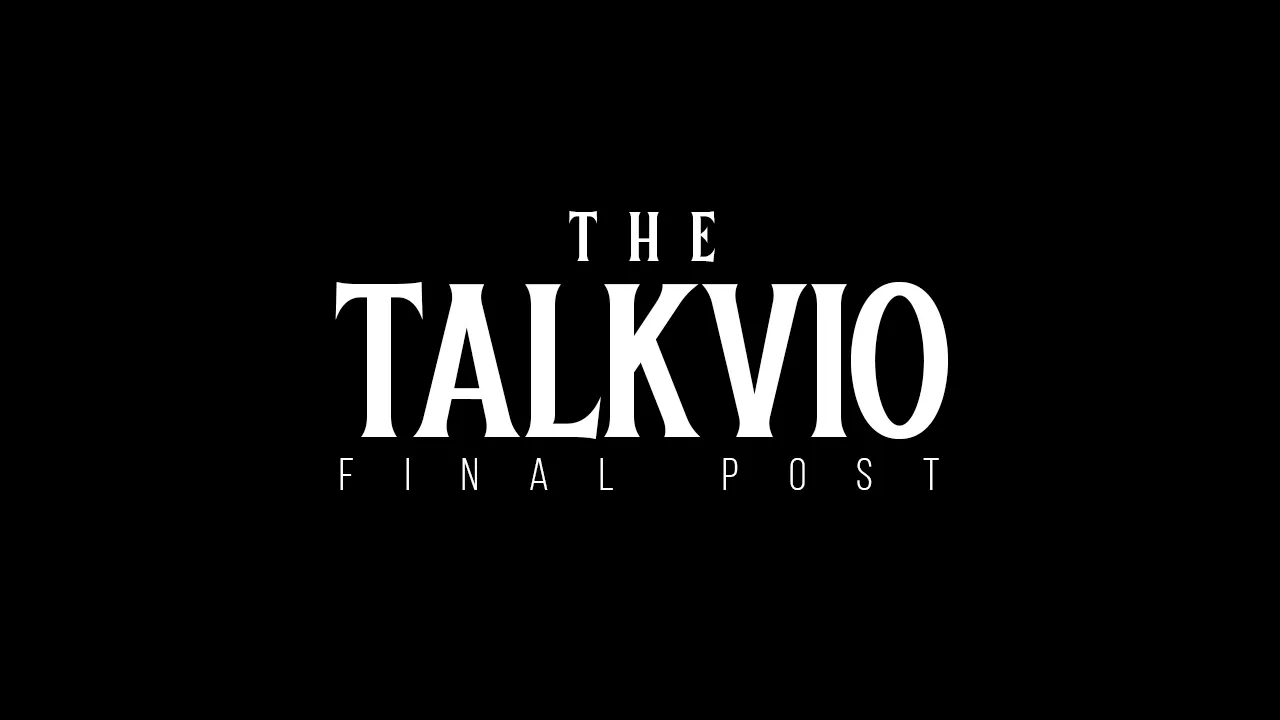
Хочу взять актуальный пример.
Недавно вышедший «Изгоняющий дьявола: Верующий» взял очень хорошие шрифты для своих инициалов.
[КИНО-ШРИФТЫ: Экзорцист] #2
Основной шрифт, которым написано название фильма, называется «Baisteach». Его редко увидишь, но для фильма он идеально подошёл. Его нельзя использовать в коммерции и он не поддерживает кириллицу.
Второй шрифт, которым были написаны все дополнительные надписи это очень известный шрифт «Bebas Neue». Его можно бесплатно использовать где угодно, он поддерживает кириллицу, и порой он просто незаменим.
Это один из лучших шрифтов в принципе, который я сам частенько использую в своих работах.
Шрифт стильный очень.
Ты про Baisteach или про Bebas?
Я про основной.)